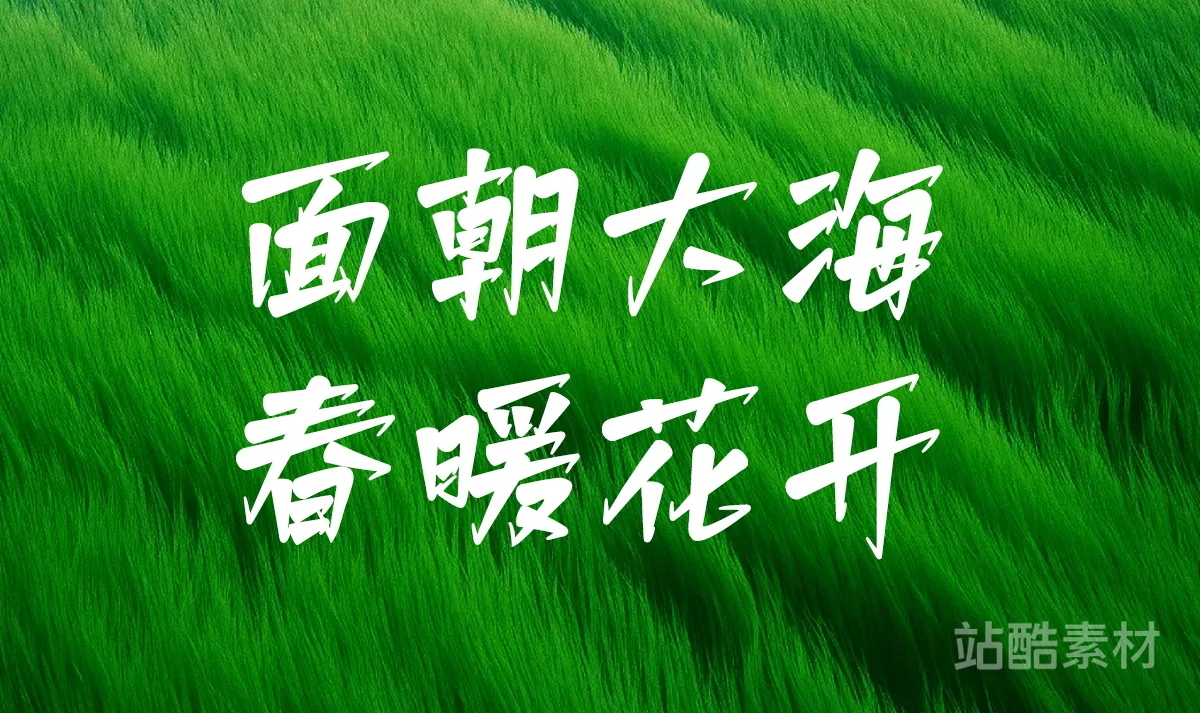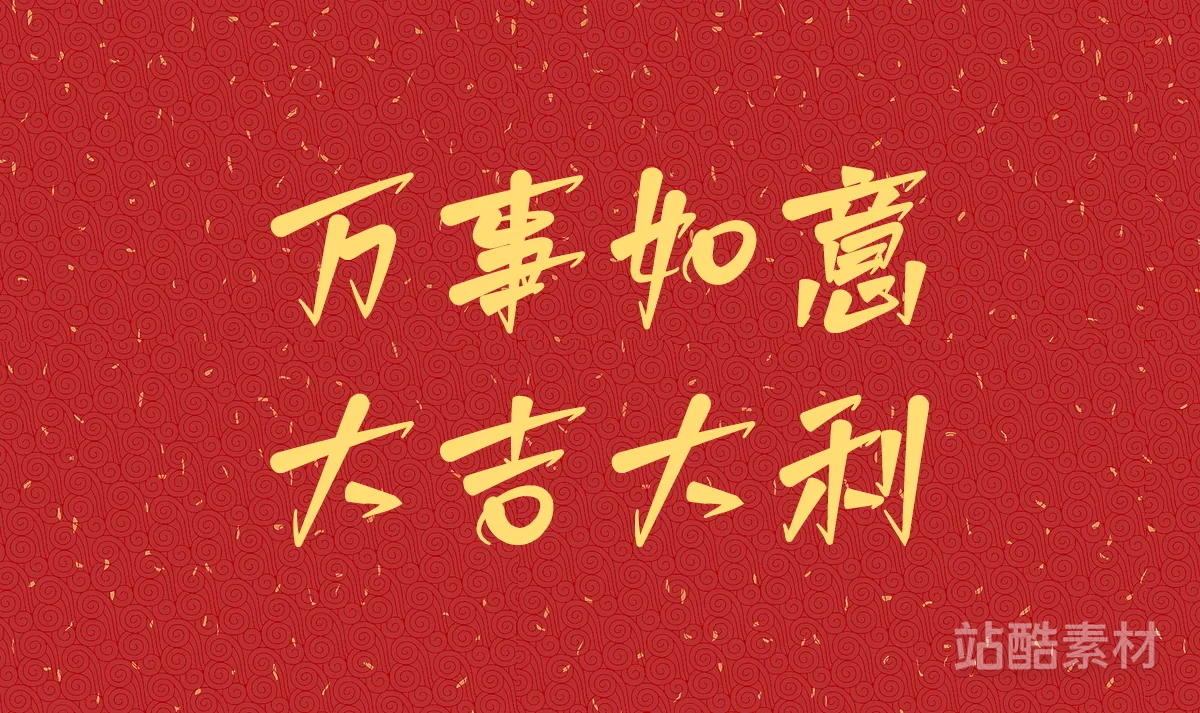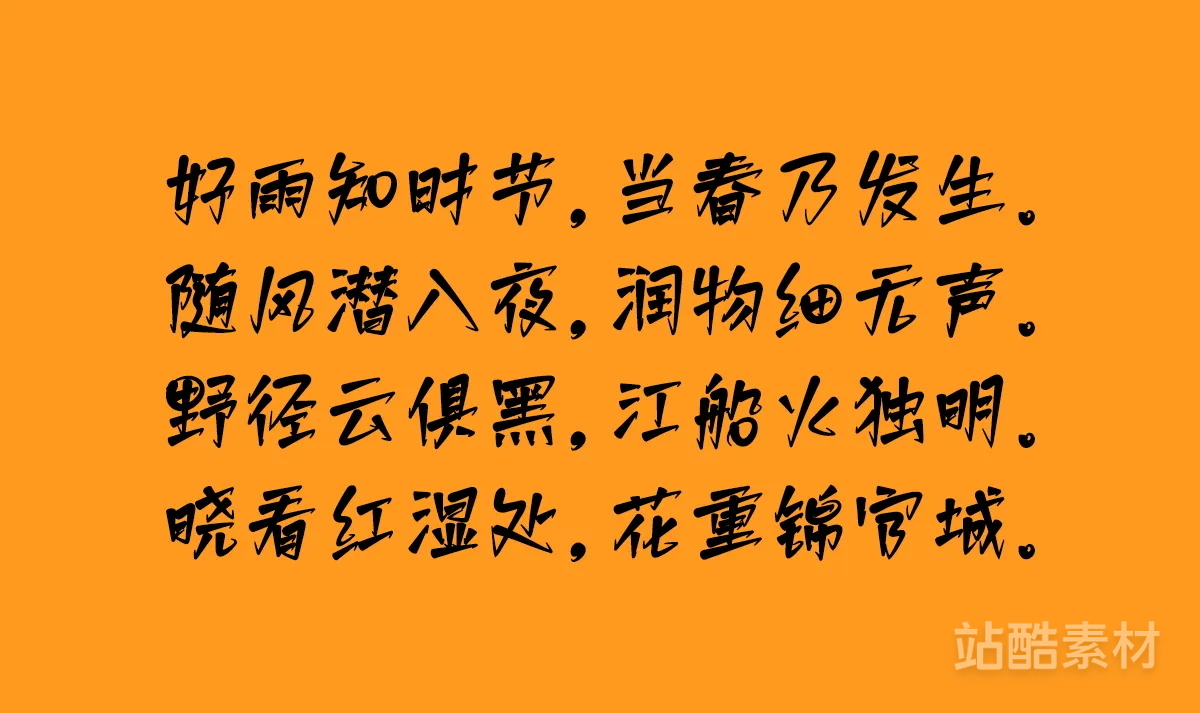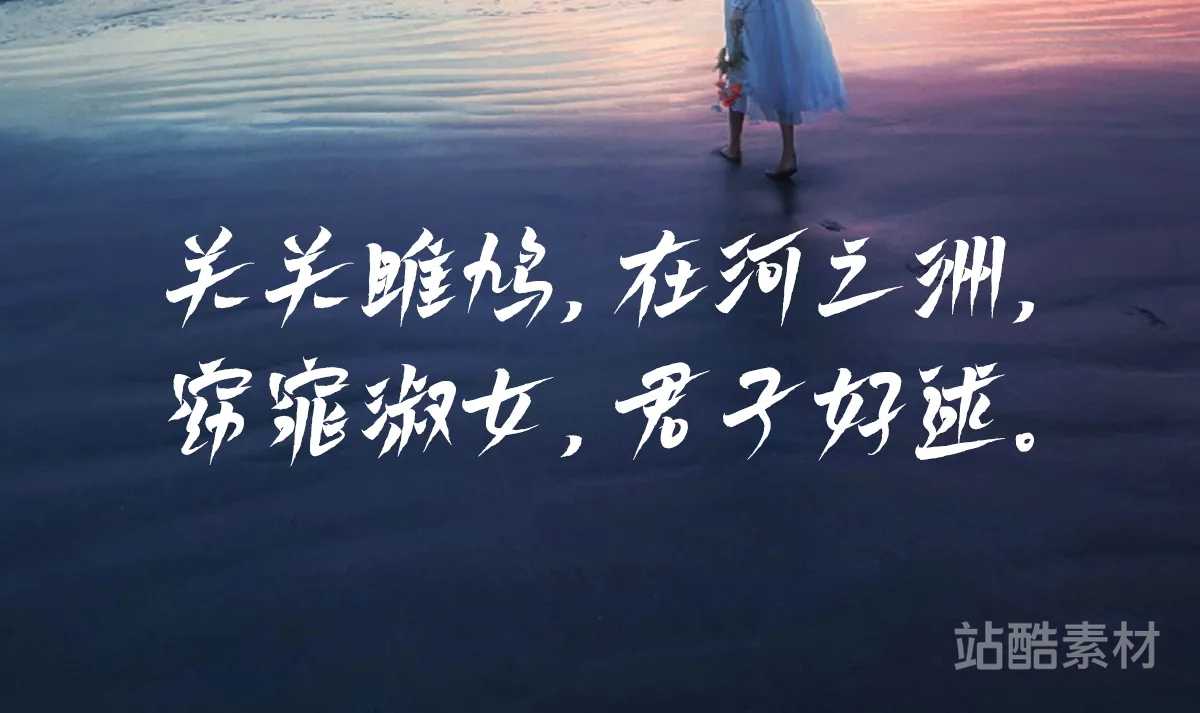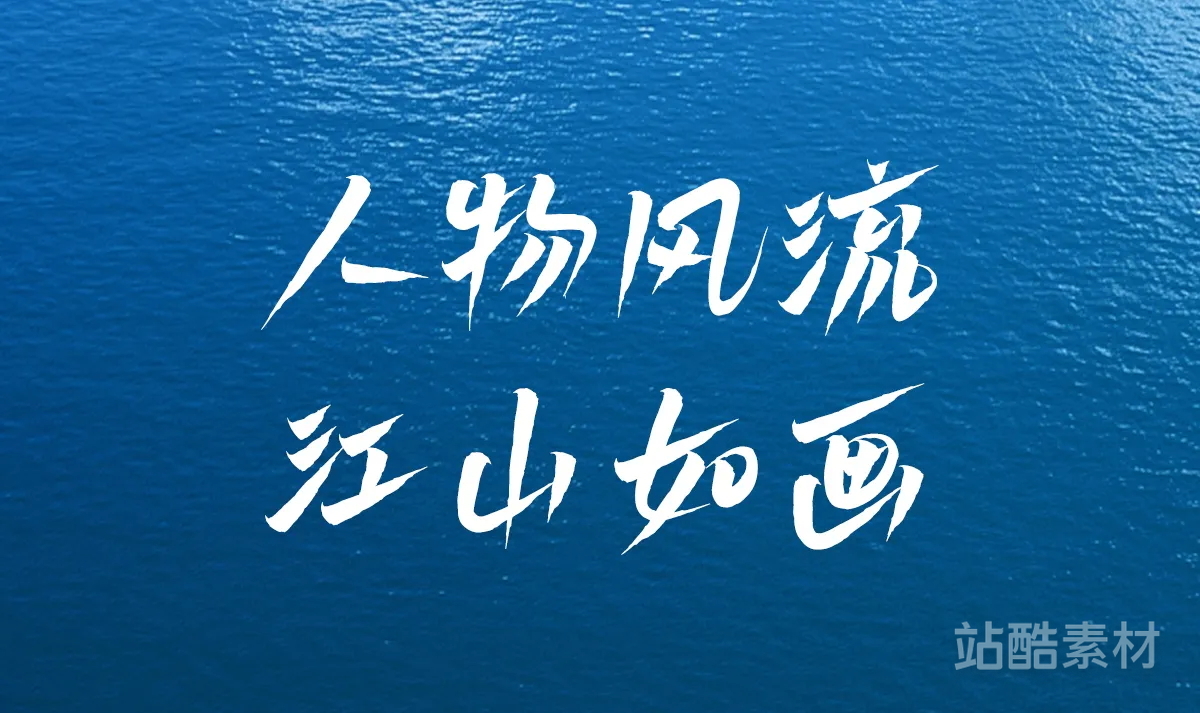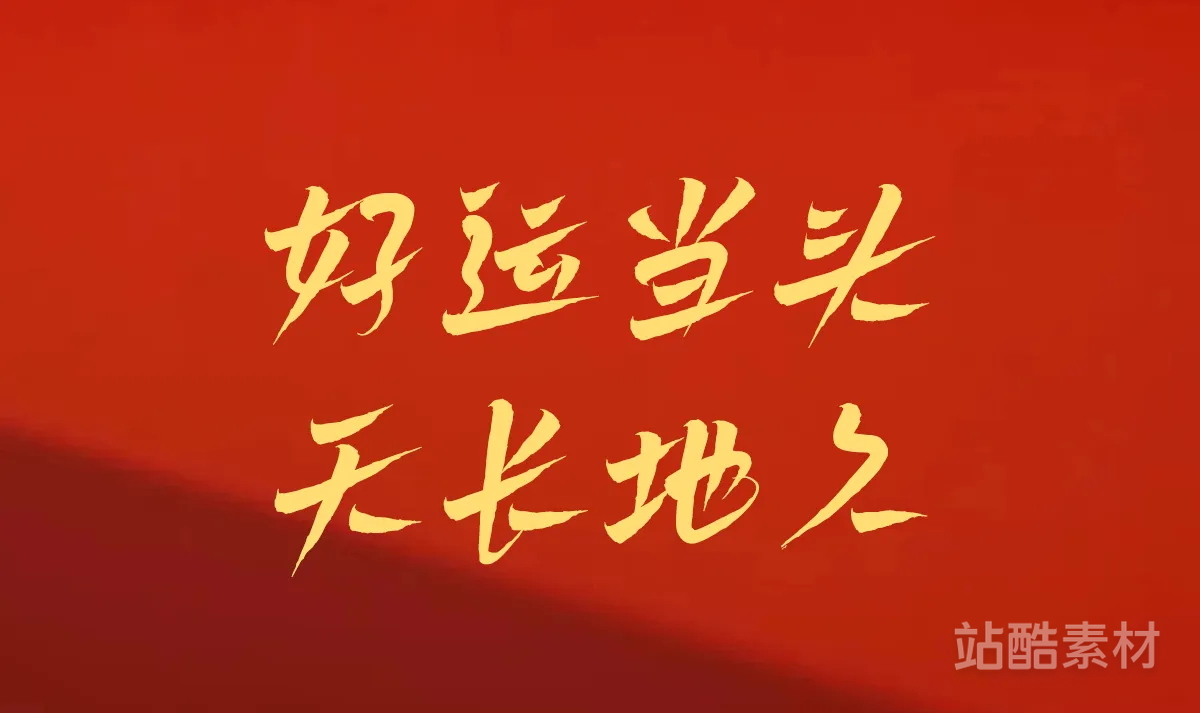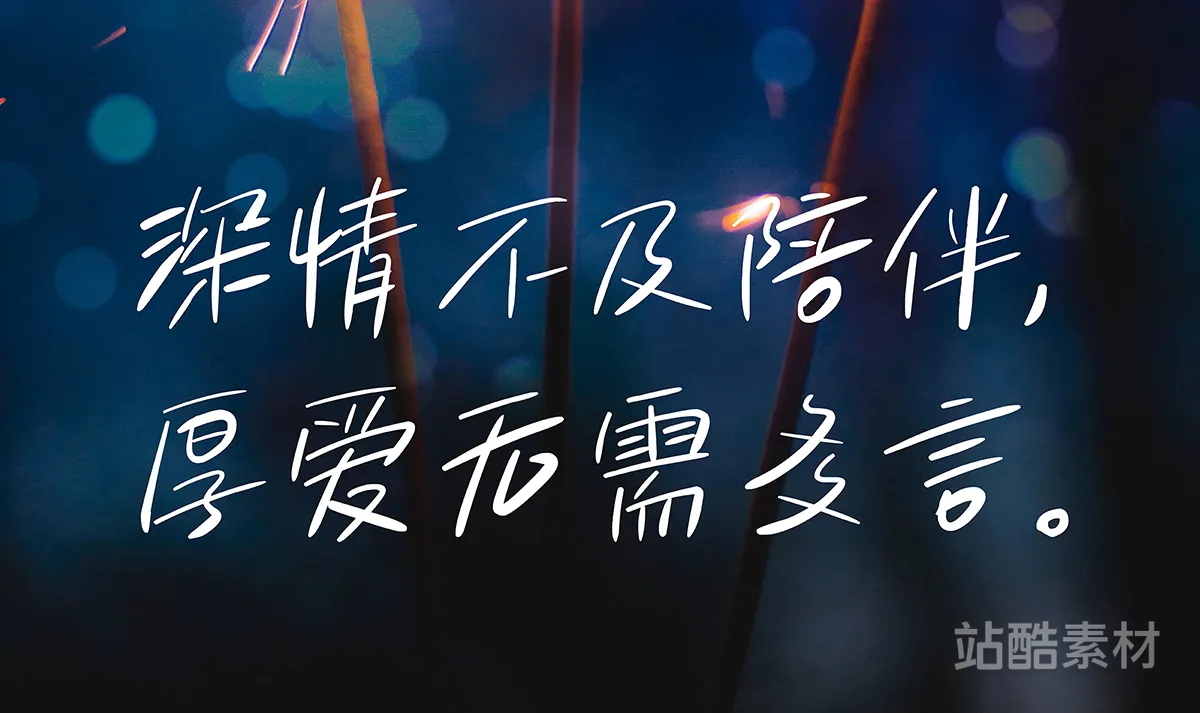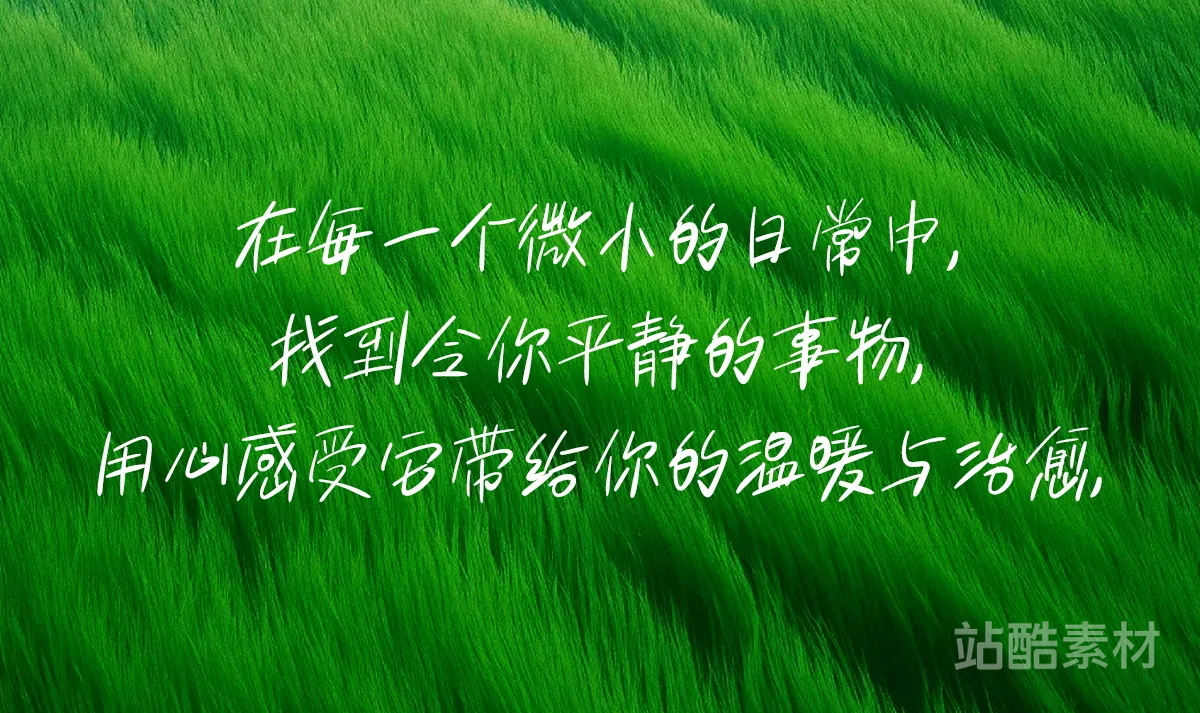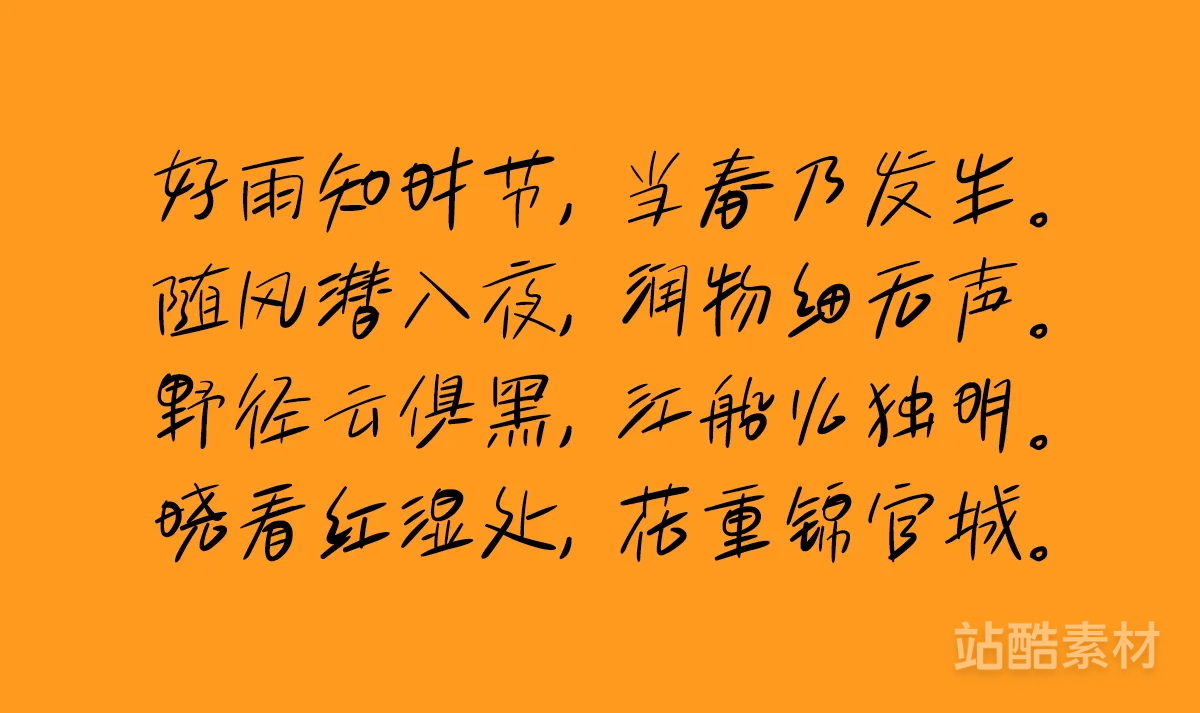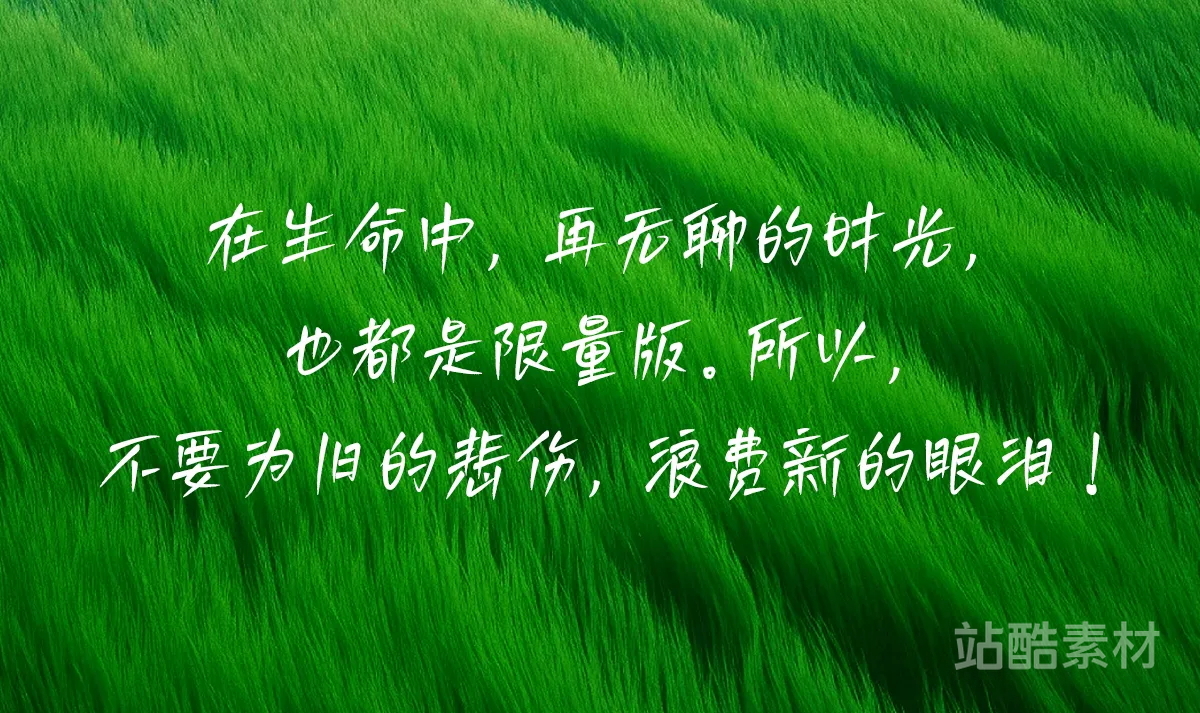
四款可免费商用的手写中文字体(作者:山人白路)
的手写字体,来自站酷用户——设计师
山人白路
白路棒棒手写体是设计师山人白路第一次创作手写字库中的一款字,该字库风格偏文艺,近7千多字符,已注册版权,可免费商用。
白路飞云手写体是设计师山人白路第一次创作手写字库中的一款字,该字库风格偏文艺,近7千多字符,已注册版权,可免费商用。
白路彤彤手写体是设计师山人白路第一次创作手写字库中的一款字,该字库风格偏文艺,近7千多字符,已注册版权,可免费商用。
白路俏丽手写体是设计师山人白路第一次创作手写字库中的一款字,该字库风格偏文艺,近7千多字符,已注册版权,可免费商用。